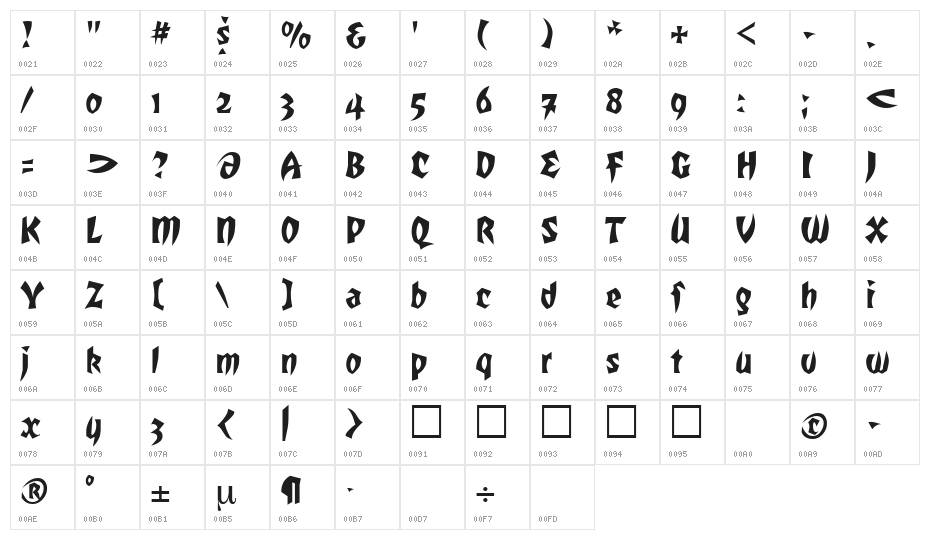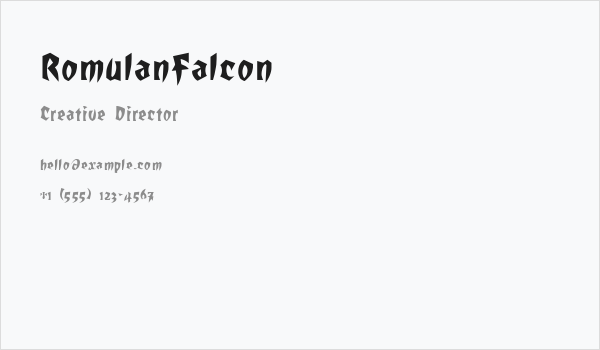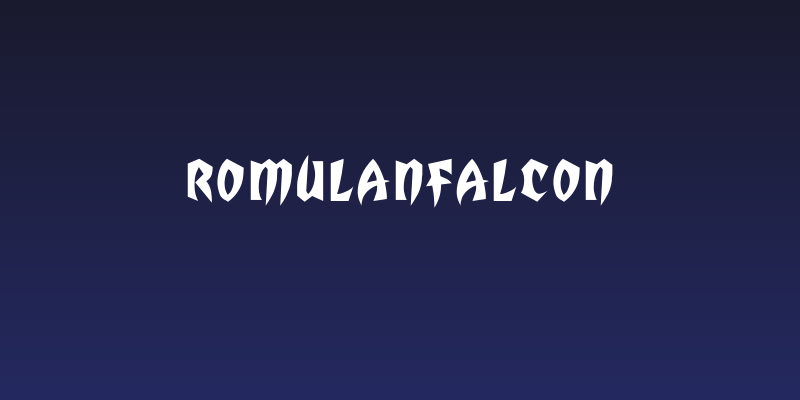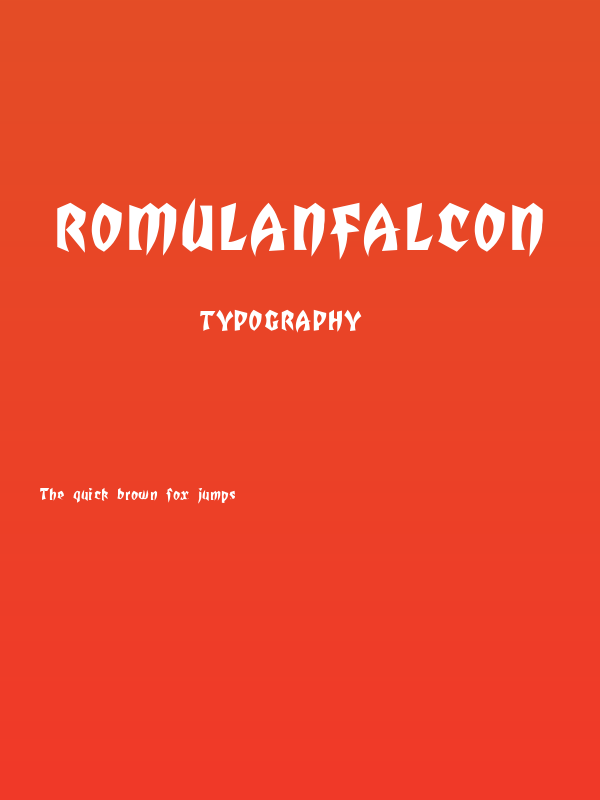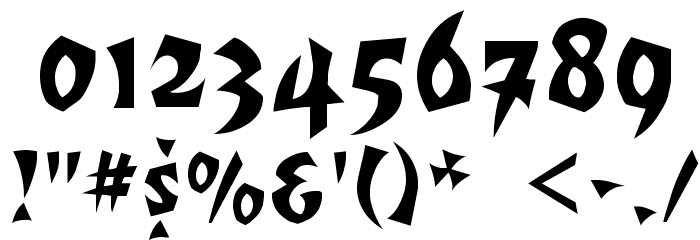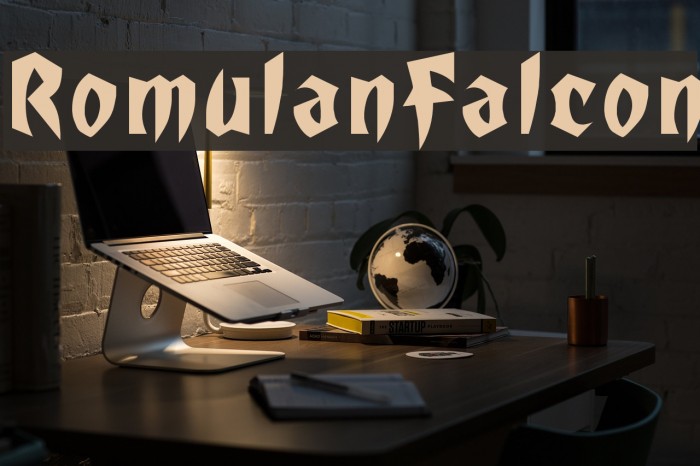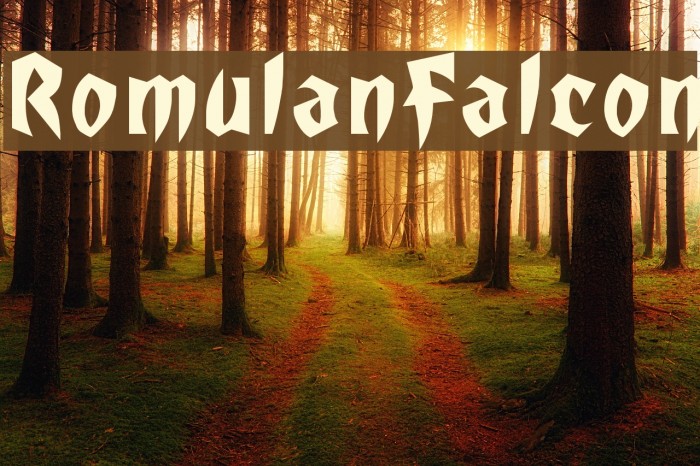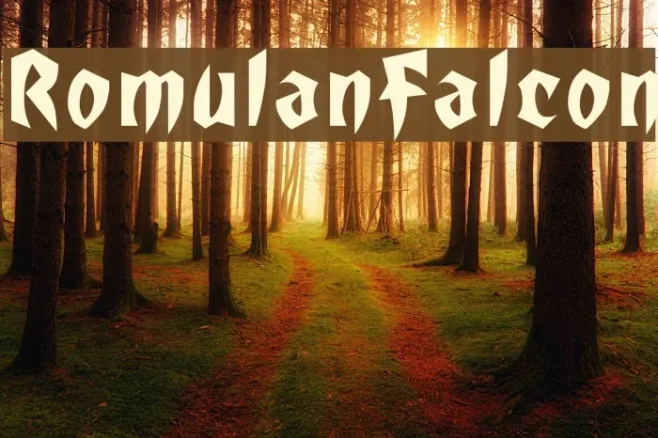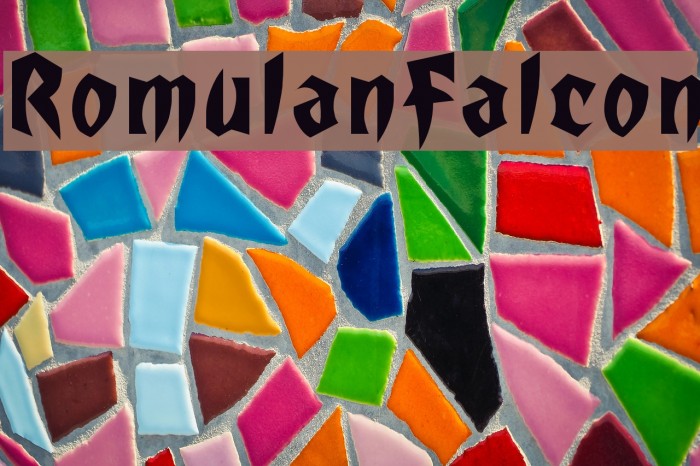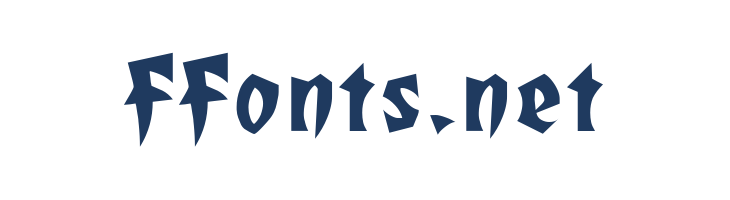
RomulanFalcon Font
| Gesamtstil | Futuristic, Tribal |
| Vorgeschlagene Projekte | Ideal for sci-fi themed designs, gaming logos, movie posters, and edgy branding materials. |